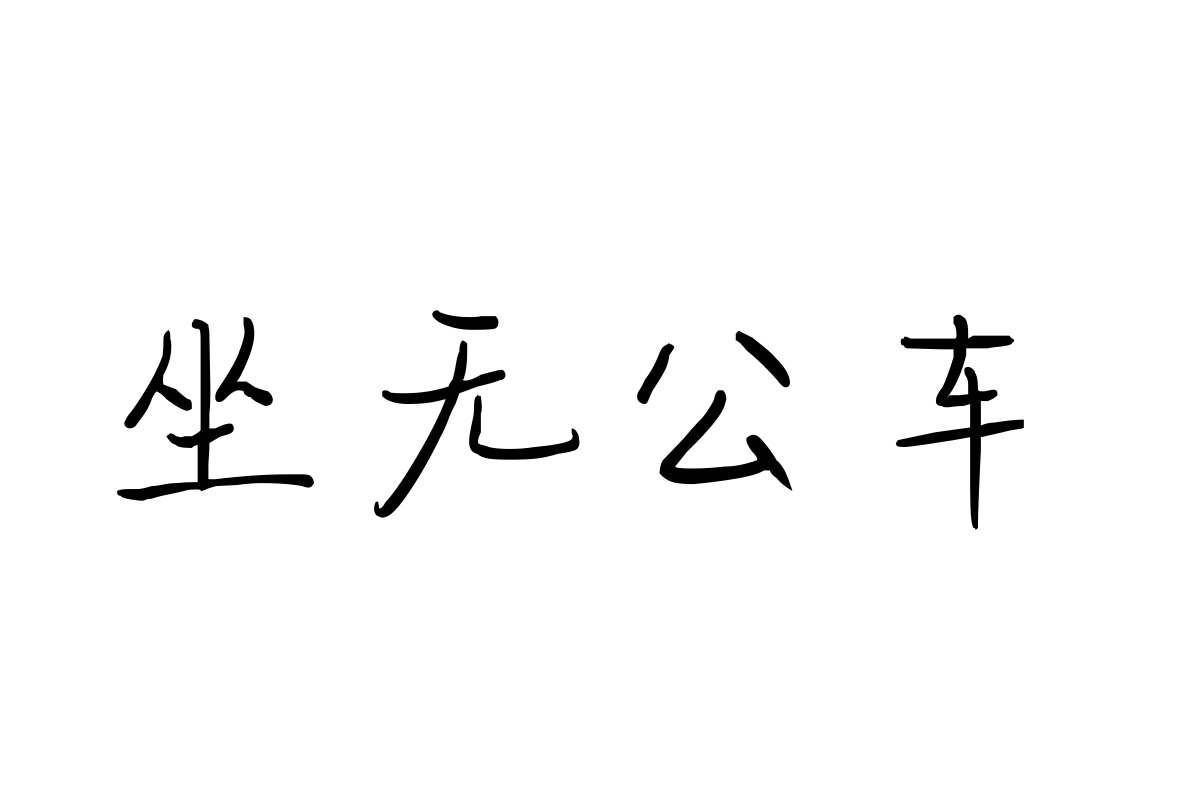
三极鲁西行楷字体是一种具有独特风格的书法字体,它融合了传统的行楷和现代的设计理念。这种字体的特点是笔画流畅、结构紧凑,给人一种简洁明快的感觉。它的线条粗细变化丰富,既有粗犷的线条,也有细腻的笔触,使得整个字体既有力量感,又不失柔美。
在设计上,三极鲁西行楷字体注重线条的连贯性和平衡性,使得整体看起来既有序又富有动感。同时,它也很好地保留了传统行楷的一些特点,如横平竖直、方正规矩等,但又不拘泥于形式,而是通过创新的设计手法,使这种古老的字体焕发出新的活力。
总之,三极鲁西行楷字体是一种集古典与现代于一身的书法字体,它既有深厚的文化底蕴,又具有现代的审美观念。无论是用于书籍、报纸、杂志还是广告宣传,都能展现出独特的艺术魅力。